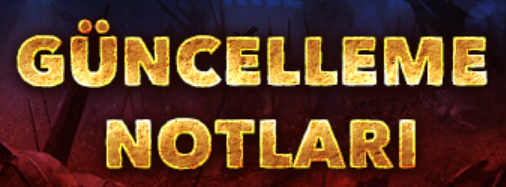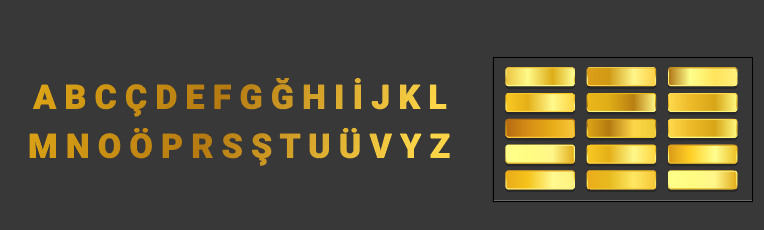
bu tarz bir yazı tipi şeklinde alfabe alınacaktır ücretli ücretsiz teşekkürler
Normal bir yazı fontunu en kalın haline getirip (misal roboto Black) Golden gradient vererek ona yakın hale getirebilirsin. Ya da Desen uygulayarak da yapabilirsin
Bunu böylece atıyım istersen İstediğin Gradyanı kullanırsın projede